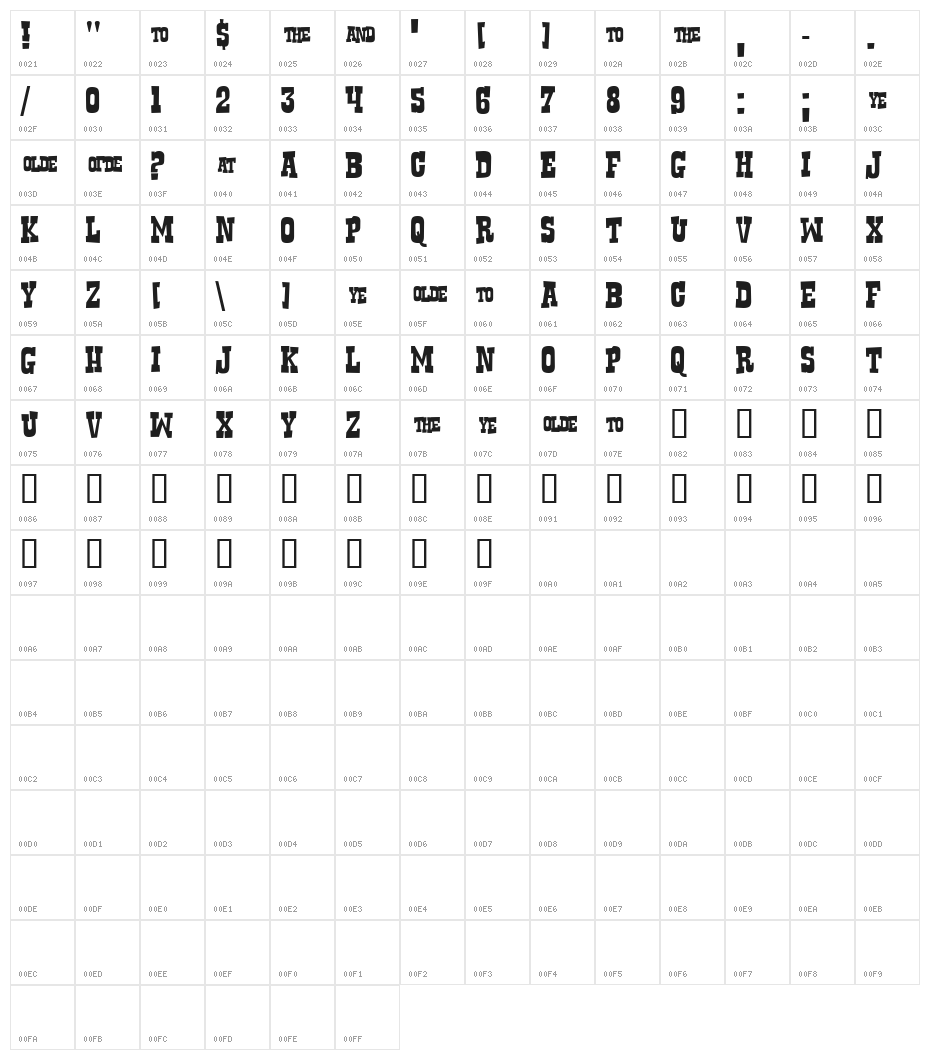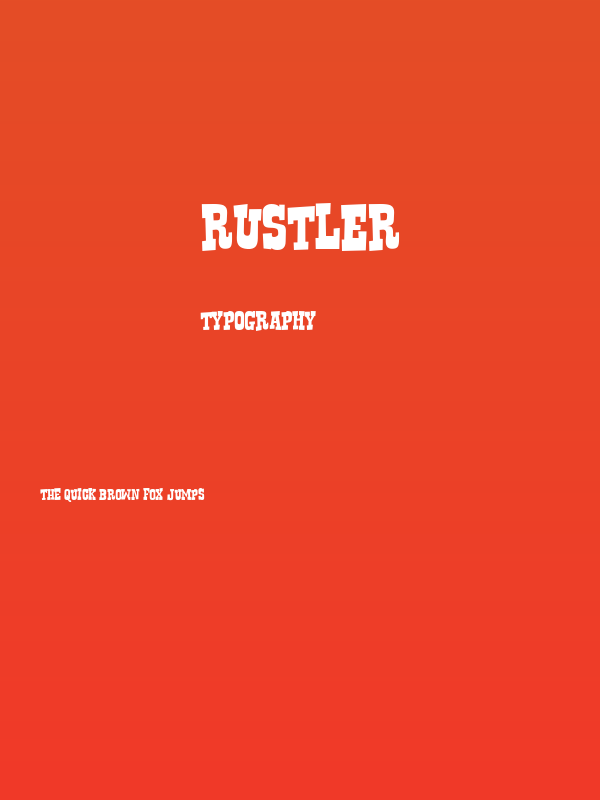
Rustler Font
| समग्र शैली | Vintage |
| उपयोग का मामला | Headlines, Logos, Posters |
| सुझाए गए प्रोजेक्ट | Ideal for posters, branding, logos, and any design requiring a strong, vintage Western feel. |